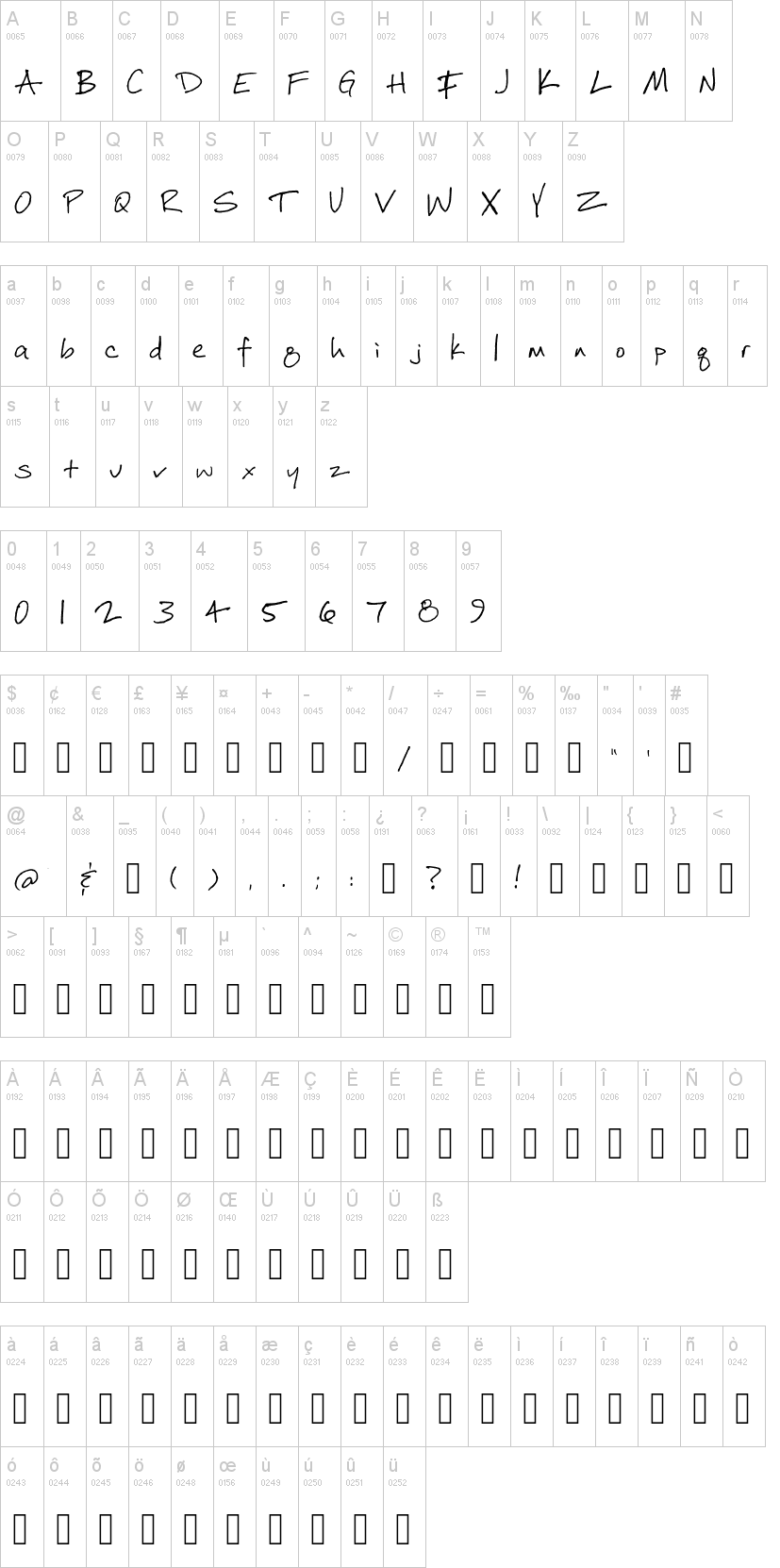
Duncans Hand
? Duncans Hand 是一款由英国设计师 Duncan Long 创作的手写体字体,它的特点是字形粗犷,细节丰富,给人以活泼自然的感觉。它的字母尺寸大,比较宽松,容易识别,适合用于网页标题、商标、海报、书籍封面等,可以给设计师提供很多创意空间。
Duncans Hand是一款非常不错的手写艺术字体,具有很好的视觉感,适合于文化类的宣传设计、商业类品牌的广告和产品包装设计以及个性化文字排版等较多场景。
Duncans Hand字符映射图